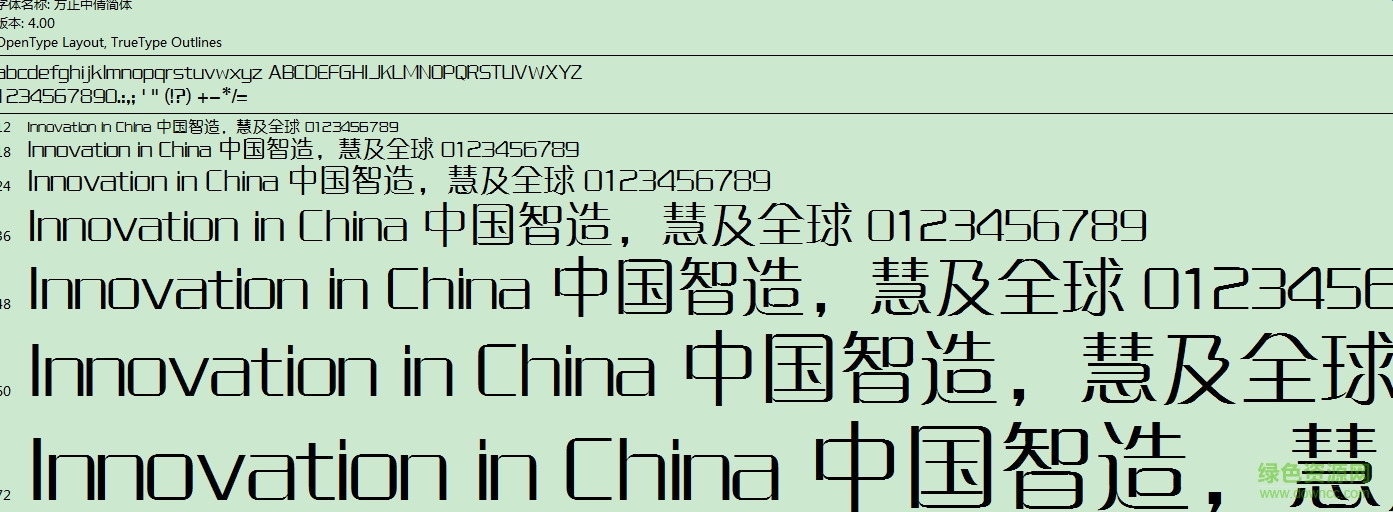
fzzqjw gb10字體是一款方正字體中非常專業(yè)字體的一種,這款字體也叫方正中倩體,用途非常廣泛,有需要的就來綠色資源網(wǎng)下載吧!
fzzqjw gb10字體介紹
fzzqjw gb10字體是很多朋友都在尋找的一款字體,小編為大家提供免費下載。字體邊緣采用了藝術(shù)形態(tài),更加耐看。做美工、藝術(shù)廣告設(shè)計的朋友不要錯過喲,快來綠色資源網(wǎng)踴躍下載吧!